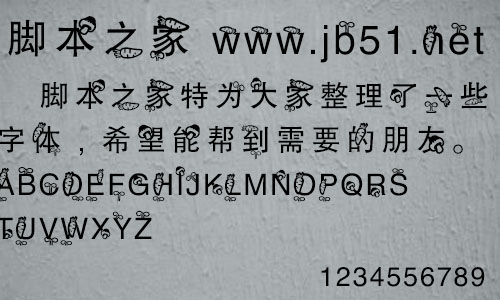
Aa纖纖維C體一款不錯(cuò)的藝術(shù)字體,由Aa字庫(kù)出品,字體筆觸適中,字體端正,字體以蘿卜和書寫的卡通圖案進(jìn)行點(diǎn)綴,適合應(yīng)用于藝術(shù)設(shè)計(jì)、平面宣傳設(shè)計(jì)、網(wǎng)頁(yè)設(shè)計(jì),書法字帖等領(lǐng)域,需要的朋友可以前來(lái)本站下載。